Как согласовать латинские и греческие буквы в одном макете
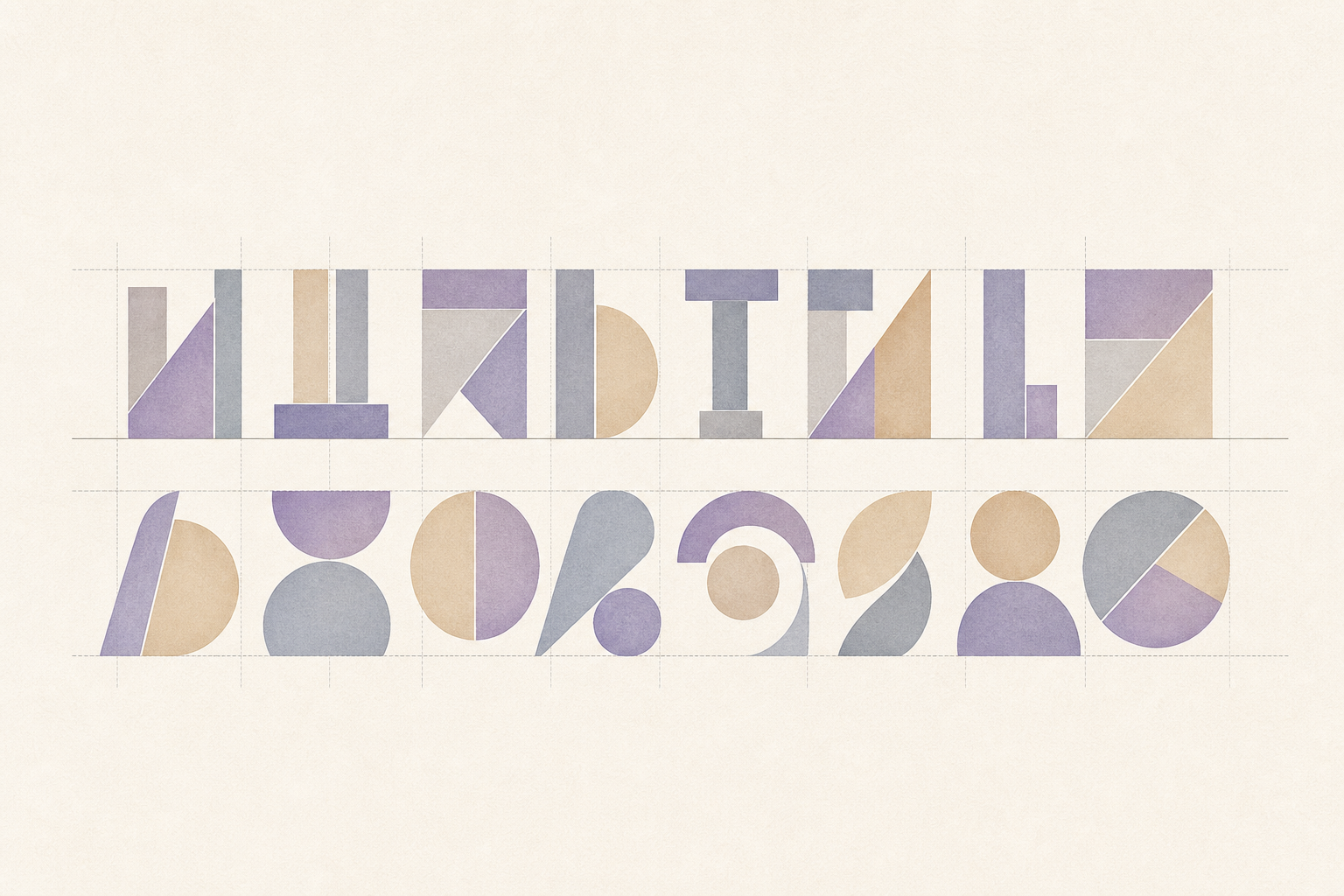
Латинские и греческие буквы согласуются в одном макете тогда, когда у них совпадают визуальная логика, базовая линия, относительная высота, насыщенность и характер деталей. Сначала сравните пропорции и начертание, затем настройте размеры и интервалы на реальных словах, а не на отдельных знаках. Ниже — пошаговая система проверки для логотипов, интерфейсов и печатных материалов.
Почему латиница и греческий алфавит выглядят несогласованно
Несогласованность возникает не только из-за разного рисунка букв. Даже два шрифта одного семейства могут заметно расходиться по высоте строчных, ширине знаков, контрасту штрихов и расстоянию между буквами. Особенно это заметно в коротких названиях, формулах, навигации и логотипах, где глаз сразу сравнивает соседние символы.
У латинского и греческого алфавитов есть похожие знаки, но их нельзя автоматически считать взаимозаменяемыми. Латинская A и греческая Α могут иметь разную геометрию, латинская B и греческая Β — разную пластику, а латинская P и греческая Ρ — отличающуюся форму и оптический вес. В математической записи такая подмена особенно опасна: символы могут выглядеть одинаково, но означать разное.
Начните с проверки поддержки греческих символов
Первый шаг — убедиться, что выбранный шрифт действительно содержит греческий набор, а не заменяет отсутствующие знаки системным шрифтом. Подмена часто проявляется по деталям: другой контраст, непривычная форма акцентов, отличающаяся толщина линий или иная высота букв. В браузере это может быть менее заметно, чем в логотипе, поэтому проверяйте макет в том окружении, где он будет использоваться.
- Проверьте наличие прописных и строчных греческих букв, если нужны оба регистра.
- Убедитесь, что в шрифте есть диакритика и политонические знаки, если текст на греческом требует их.
- Сравните начертания Regular, Medium, Bold и Italic, а не только базовый стиль.
- Проверьте цифры, математические операторы и специальные символы в том же шрифтовом файле.
- Откройте тестовую строку в целевом редакторе и убедитесь, что не происходит автоматическая подмена шрифта.
Сравните метрики: базовую линию, высоту и ширину
Согласование начинается с метрик. Базовая линия должна оставаться общей, чтобы буквы визуально стояли на одной поверхности. Затем сравните высоту прописных, высоту строчных и выступающие элементы. У греческих знаков могут быть другие верхние и нижние выносные элементы, поэтому одинаковый кегль не гарантирует одинаковый визуальный размер.
Оценивать нужно не только реальные измерения, но и оптическую высоту. Например, круглая Θ может казаться ниже прямоугольной H, а широкая Ω — тяжелее узкой латинской W. Если греческая часть выглядит мельче, сначала попробуйте увеличить ее размер на небольшую величину. Если это не помогает, корректируйте не масштаб, а межбуквенное расстояние и насыщенность.
Как проверять буквы на одной строке
Составьте несколько тестовых строк: «Alpha Αlpha», «TYPE ΤΥΡΕ», «E = mc²», «Μικρό κείμενο» и «Design Δesign». Такие примеры помогают увидеть, где латиница и греческий алфавит расходятся по высоте, ширине и ритму. Для логотипа используйте реальные слова бренда, а для интерфейса — заголовок, подпись, кнопку и числовое значение.
Согласуйте конструкцию и характер знаков
Хорошая пара шрифтовых наборов сохраняет общий характер: одинаковую степень геометричности, близкий контраст, сходную пластику окончаний и сопоставимую открытость форм. Если латинские буквы построены на строгих прямых и кругах, греческие знаки не должны выглядеть каллиграфическими. Если латиница гуманистическая и мягкая, чрезмерно механистичная греческая часть разрушит единство.
Особое внимание уделите буквам, которые визуально повторяют латинские формы. В греческом тексте это Α, Β, Ε, Ζ, Η, Ι, Κ, Μ, Ν, Ο, Ρ, Τ, Υ и Χ в верхнем регистре. Их рисунок должен соответствовать общей системе шрифта, но не обязан буквально копировать латинские знаки. Небольшие отличия в терминалах и пропорциях помогают сохранить узнаваемость алфавита.
Проверяйте насыщенность, контраст и толщину штрихов
Если греческие буквы кажутся темнее латинских, проблема может быть в распределении черного, а не в номинальной толщине. Круглые формы и диагонали по-разному воспринимаются глазом, поэтому одинаковое значение начертания не всегда дает одинаковый цвет строки. Сравните фрагменты в масштабе, в котором их увидит пользователь, и при необходимости выберите соседнее начертание или слегка измените размер.
Настройте кернинг и межбуквенные интервалы
Автоматический кернинг может хорошо работать внутри одного алфавита и давать слабый результат на границе латиницы и греческого. Причина — в том, что такие пары не всегда предусмотрены таблицами шрифта. Проверьте соседства вроде A–Α, E–Μ, T–Υ, X–Χ, а также сочетания греческих строчных с латинскими цифрами и знаками пунктуации.
Не исправляйте весь текст увеличением трекинга. Межбуквенный интервал должен поддерживать ритм конкретной строки: заголовку может требоваться более плотная посадка, а капительному логотипу — чуть больше воздуха. Отдельные пары лучше корректировать вручную, особенно рядом с круглыми, диагональными и скошенными формами.
Чтобы согласовать латинские и греческие буквы в одном макете, проверяйте не отдельные символы, а всю систему: поддержку Unicode, базовую линию, оптическую высоту, пропорции, насыщенность, кернинг и реальный текстовый контекст. Начинайте с одного качественного шрифтового семейства, а раздельные гарнитуры используйте только при понятной композиционной задаче.